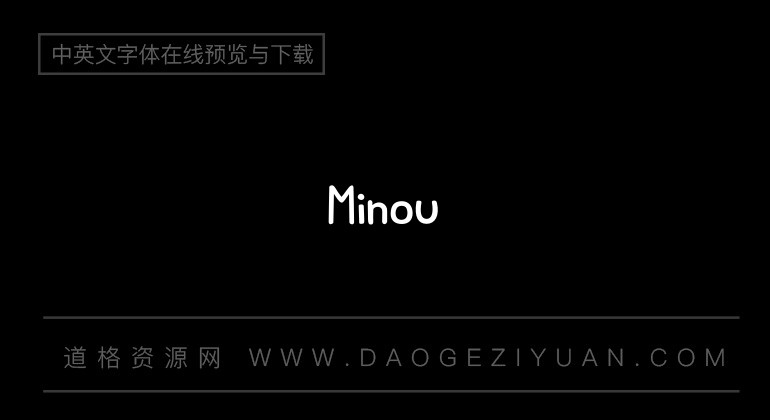
Minou
Minou是一种优雅精致的手写字体,由设计师Joana Correia于2019年创作。这个字体的特点是其流畅的笔画和自然的手写风格,适合用于卡片、海报、印刷品和数字设计等多种场合。 Minou字体具有丰富的变体和字形,包括三种不同的大小写字母,以及大量的升降元音和重音符号,使得这个字体可以使用多种语言。此外,Minou还包括一些独特的装饰元素,如花朵和叶子,可以用来增强设计的美感和吸引力。 总之,Minou是一种精美的手写字体,适用于许多不同的设计项目和应用程序。
Minou是一款非常不错的手写艺术字体,具有很好的视觉感,适合于文化类的宣传设计、商业类品牌的广告和产品包装设计以及个性化文字排版等较多场景。